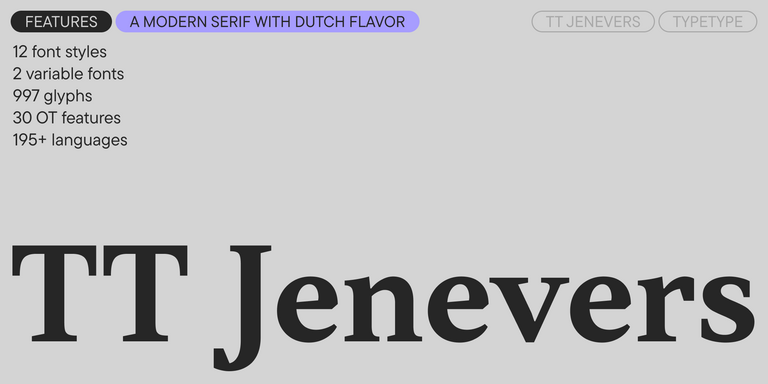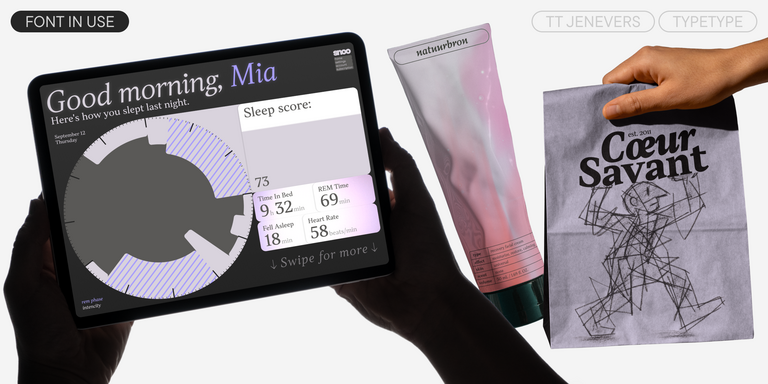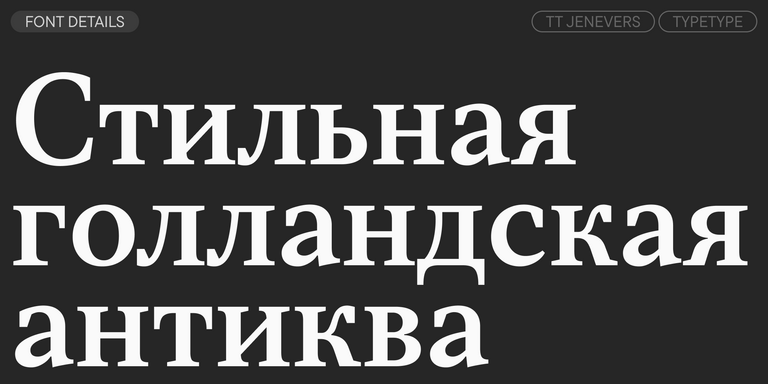
TT Nooks Serif — акцидентная новостильная антиква с лёгким налётом эгоцентричности. У неё острый и твёрдый, при этом элегантный и статный характер.
Шрифты похожие на FF DIN Slab
Если вы устали от «заезженных» шрифтов и ищете гарнитуры, похожие на FF DIN Slab, ознакомьтесь с нашими лучшими альтернативами FF DIN Slab. Это шрифты, которые имеют близкие характеристики, но в то же время обладают новыми уникальными особенностями дизайна. Например, относятся к той же категории шрифтов, подходят для тех же целей и имеют похожие черты, но отличаются в деталях или пропорциях.
Найдите отличную замену FF DIN Slab и попытайтесь имитировать похожее настроение, передать нужное вам ощущение, используя его в своих проектах. Каждый шрифт, представленный на этой странице, является двойником шрифта FF DIN Slab, фактически его полным аналогом.
TT Jenevers стилистически относится к голландским антиквам нового стиля. В гарнитуре присутствуют характерные детали, свойственные голландским антиквам — это ассиметричная форма засечек или нерегулярный наклон овалов.
TT Ramillas — стильная и современная антиква. Включает уникальные декоративные начертания и буквицы с цветочным орнаментом.
TT Espina — дисплейная антиква с выразительными засечками. При ее создании дизайнеры вдохновлялись исторической формой буквы «O», которая приобретала ромбовидную форму из-за качества печати. В каждую букву хочется всматриваться, так что заголовки, оформленные TT Espina, точно привлекут внимание.
TT Marxiana является проектом по реконструкции набора дореволюционных шрифтов, которые использовались в изготовлении и печати журнала «Нива» 1887 года выпуска, а именно на его антикве и италике, гротеске и эльзевире.
TT Tsars является коллекцией акцидентных титульных антиквенных шрифтов, стилизованных под начало, середину и конец XVIII века. В основу проекта легли титульные шрифты, то есть те шрифты, которыми оформлялись, в частности, книжные титулы.